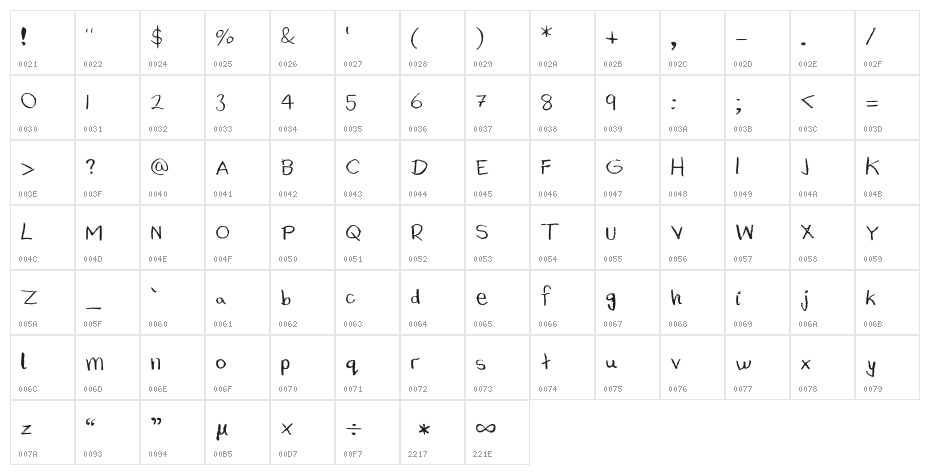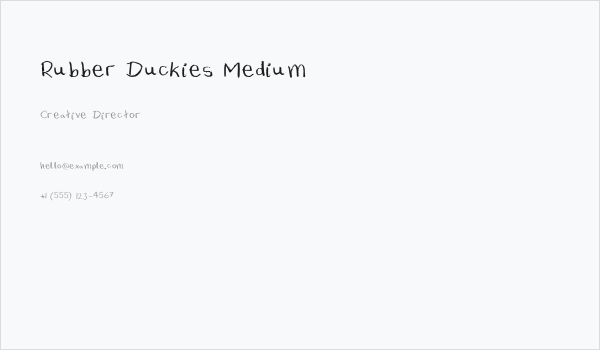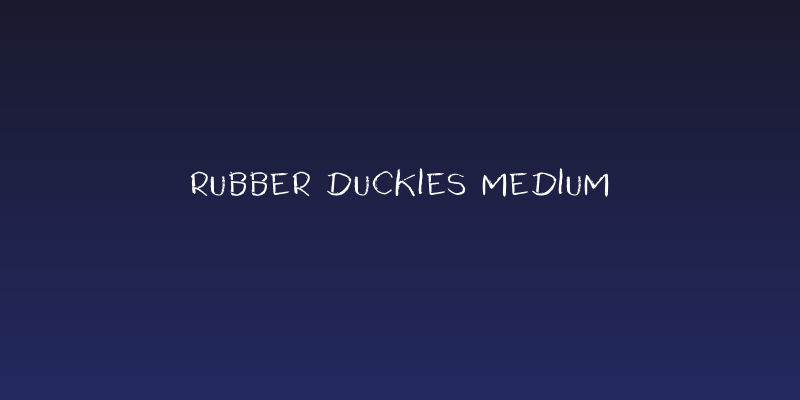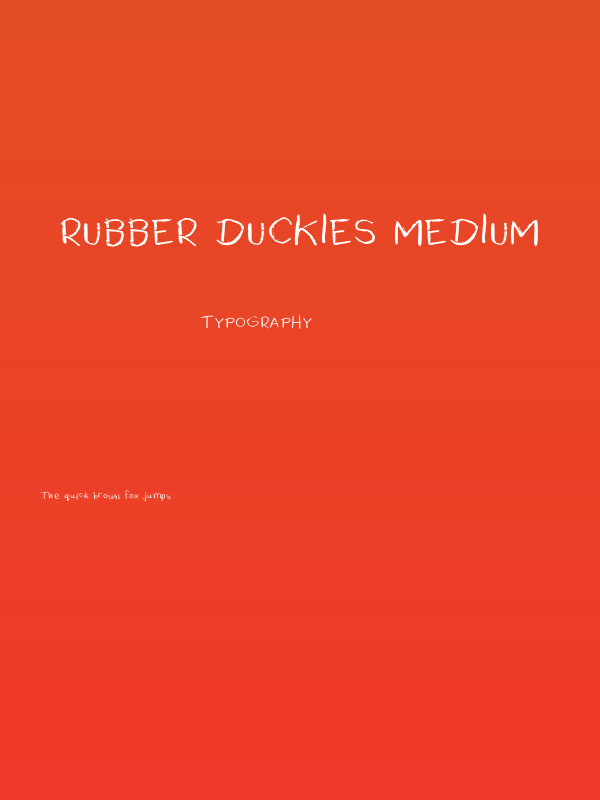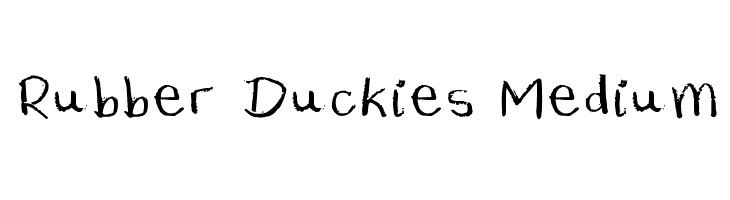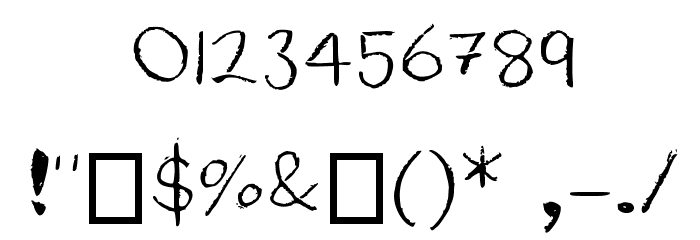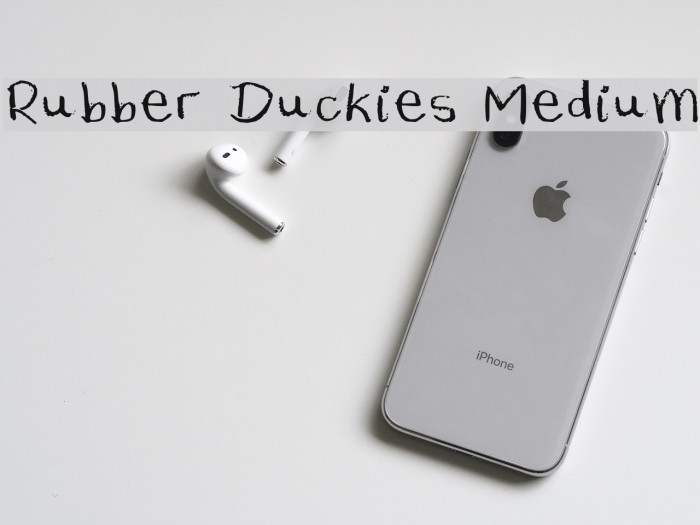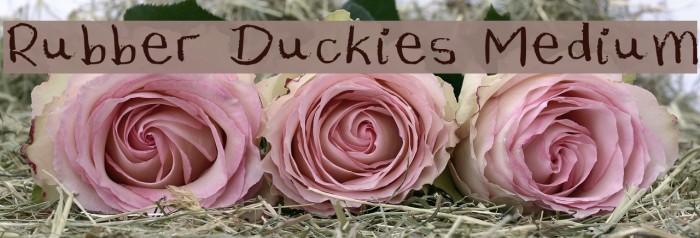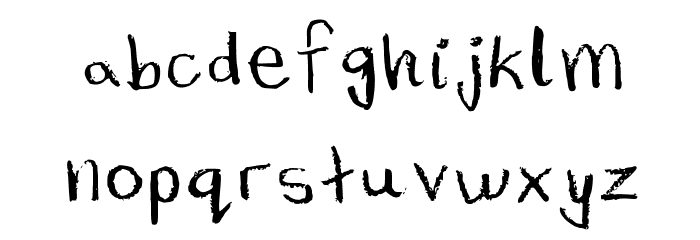
Rubber Duckies Medium Font
| Gesamtstil | Playful, Casual |
| Anwendungsfall | Headlines, Logos, Creative projects |
| Vorgeschlagene Projekte | Ideal for children's books, playful branding, greeting cards, and creative posters. |